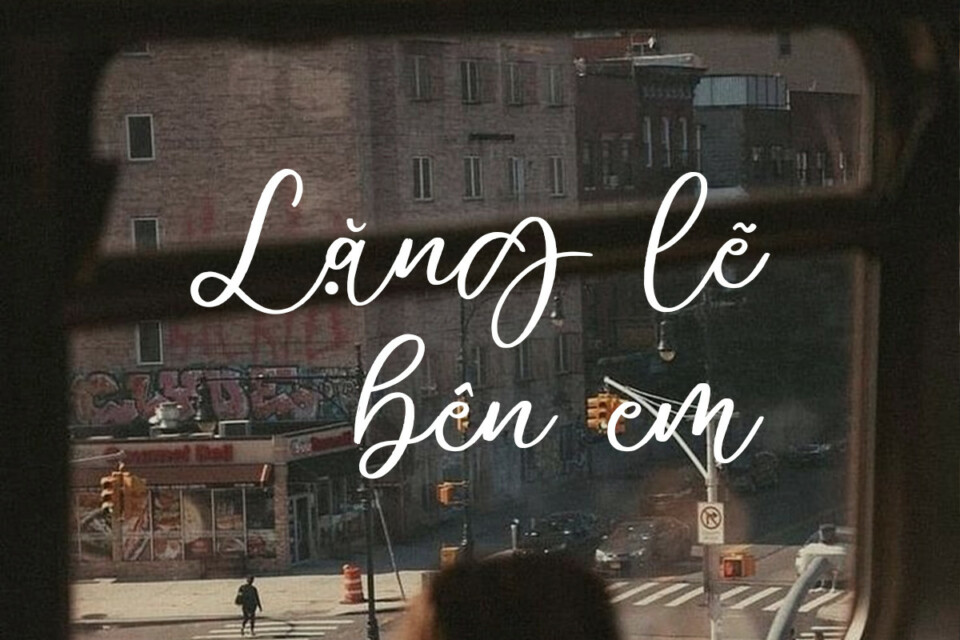
Trong thế giới thiết kế đồ họa đầy màu sắc và không ngừng biến đổi, việc lựa chọn một Font Chữ phù hợp có thể tạo nên sự khác biệt đáng kể cho tác phẩm của bạn. Đặc biệt, với sự phát triển của ngành thiết kế tại Việt Nam, nhu cầu về các bộ font được việt hóa chất lượng ngày càng tăng cao. Và chính tại đây, Font việt hoá MJ Maritime Wonderine nổi lên như một lựa chọn hoàn hảo, mang đến vẻ đẹp cổ điển pha chút hiện đại, phù hợp cho vô vàn ý tưởng sáng tạo từ logo, bao bì, thiệp mời cho đến các ấn phẩm truyền thông.
Giới Thiệu Chung Về Font Việt Hoá MJ Maritime Wonderine
Font việt hoá MJ Maritime Wonderine không chỉ là một kiểu chữ thông thường; nó là sự kết hợp tinh tế giữa phong cách script mềm mại và nét đặc trưng của kiểu chữ viết tay cổ điển. Được lấy cảm hứng từ những lá thư cũ kỹ, các bản đồ hàng hải hay những dòng chữ viết trên các tấm bảng hiệu vintage, MJ Maritime Wonderine mang đến một luồng gió mới, độc đáo và đầy cảm xúc. Sự việt hóa cẩn thận giúp font này trở nên thân thiện hơn với người dùng Việt Nam, đảm bảo rằng mọi ký tự, dấu câu và thanh điệu đều được hiển thị một cách chính xác và đẹp mắt, giữ nguyên tinh thần gốc của font.
Bộ font này đặc biệt phù hợp với những ai đang tìm kiếm sự tinh tế, thanh lịch nhưng không kém phần mạnh mẽ. Với các dự án cần nhấn mạnh vào yếu tố cá nhân hóa, sự hoài cổ hoặc một chút phong cách bohemian, MJ Maritime Wonderine chắc chắn sẽ là một công cụ đắc lực. Các nhà thiết kế web, biên tập viên tạp chí, chủ cửa hàng đồ thủ công hay những người làm sự kiện đều có thể tận dụng vẻ đẹp của font này để tạo ra những sản phẩm nổi bật, thu hút ánh nhìn ngay từ cái chạm đầu tiên.
Điểm Nổi Bật Và Ứng Dụng Đa Dạng Của MJ Maritime Wonderine
Điều làm nên sức hấp dẫn của Font việt hoá MJ Maritime Wonderine chính là sự đa dạng trong phong cách và tính linh hoạt trong ứng dụng. Bộ font này sở hữu các nét chữ mềm mại, uyển chuyển với những đường cong tự nhiên, tạo cảm giác như được viết tay một cách tỉ mỉ. Các phiên bản việt hóa đã được tối ưu hóa để tương thích hoàn hảo với tiếng Việt, bao gồm đầy đủ các ký tự có dấu, giúp người dùng không còn lo lắng về lỗi hiển thị hay mất nét khi sử dụng.
- Thiết Kế Logo và Nhận Diện Thương Hiệu: Mang lại vẻ đẹp độc đáo, tạo ấn tượng mạnh mẽ cho các thương hiệu muốn thể hiện sự cá tính, sang trọng hoặc hơi hướng vintage.
- Thiệp Mời và Ấn Phẩm Sự Kiện: Hoàn hảo cho thiệp cưới, thiệp sinh nhật, hoặc các ấn phẩm kỷ niệm, tạo cảm giác ấm áp và trang trọng.
- Bao Bì Sản Phẩm: Giúp sản phẩm nổi bật trên kệ hàng, đặc biệt là các sản phẩm thủ công, mỹ phẩm tự nhiên hoặc đồ uống cao cấp.
- Quảng Cáo và Tạp Chí: Tạo tiêu đề bắt mắt, thu hút độc giả với phong cách độc đáo, không lẫn vào đâu được.
- Thiết Kế Website và Blog: Phù hợp cho các blog cá nhân, website về thời trang, ẩm thực, hoặc các dự án sáng tạo cần sự tinh tế.
Không chỉ dừng lại ở các ký tự cơ bản, MJ Maritime Wonderine còn đi kèm với một số glyph và swash đặc biệt, cho phép người dùng tùy chỉnh và sáng tạo không giới hạn. Điều này mở ra nhiều khả năng để cá nhân hóa thiết kế, tạo ra những biến thể độc đáo mà vẫn giữ được sự đồng bộ về mặt thẩm mỹ. Bạn có thể dễ dàng kết hợp font này với các font serif hoặc sans-serif đơn giản để tạo ra sự cân bằng, làm nổi bật thông điệp chính.
Lợi Ích Khi Sử Dụng Font Việt Hoá Chất Lượng Cao
Việc sử dụng các font được việt hóa chất lượng như MJ Maritime Wonderine mang lại nhiều lợi ích thiết thực cho các nhà thiết kế và người dùng cá nhân. Đầu tiên và quan trọng nhất, nó đảm bảo tính thẩm mỹ và chuyên nghiệp cho các dự án tiếng Việt. Một font không được việt hóa đúng cách có thể gây ra lỗi hiển thị dấu, vỡ chữ, làm giảm đi đáng kể giá trị của thiết kế.
Thứ hai, các font việt hóa giúp tiết kiệm thời gian và công sức cho người thiết kế. Thay vì phải điều chỉnh từng ký tự một hoặc tìm kiếm các giải pháp tạm thời, bạn có thể dễ dàng áp dụng font vào dự án của mình và tập trung vào các khía cạnh sáng tạo khác. Điều này đặc biệt quan trọng trong các dự án có deadline gấp rút hoặc khi bạn cần tạo ra nhiều sản phẩm trong thời gian ngắn.
Thứ ba, việc sử dụng font việt hóa chất lượng cũng góp phần nâng cao trải nghiệm người dùng cuối. Độc giả sẽ dễ dàng đọc và tiếp nhận thông tin hơn khi văn bản được hiển thị rõ ràng, mạch lạc và đẹp mắt. Điều này trực tiếp ảnh hưởng đến hiệu quả truyền thông và mức độ tương tác với sản phẩm của bạn.
Cuối cùng, việc cộng đồng font Việt ngày càng phát triển với nhiều bộ font việt hóa chất lượng cao như MJ Maritime Wonderine cho thấy sự quan tâm và đầu tư vào lĩnh vực typography tại Việt Nam. Đây là một tín hiệu đáng mừng, mở ra nhiều cơ hội hơn cho các nhà thiết kế trẻ và góp phần làm phong phú thêm kho tàng tài nguyên thiết kế của quốc gia.
Tóm lại, Font việt hoá MJ Maritime Wonderine là một lựa chọn tuyệt vời cho bất kỳ ai đang tìm kiếm một kiểu chữ độc đáo, mang phong cách vintage nhưng vẫn rất hiện đại và dễ ứng dụng. Với khả năng việt hóa hoàn chỉnh và các tính năng đa dạng, font này chắc chắn sẽ là trợ thủ đắc lực giúp bạn biến những ý tưởng sáng tạo thành hiện thực, tạo ra những tác phẩm gây ấn tượng mạnh mẽ. Đừng ngần ngại khám phá và áp dụng bộ Font Chữ này vào các dự án tiếp theo của bạn để trải nghiệm sự khác biệt mà nó mang lại.